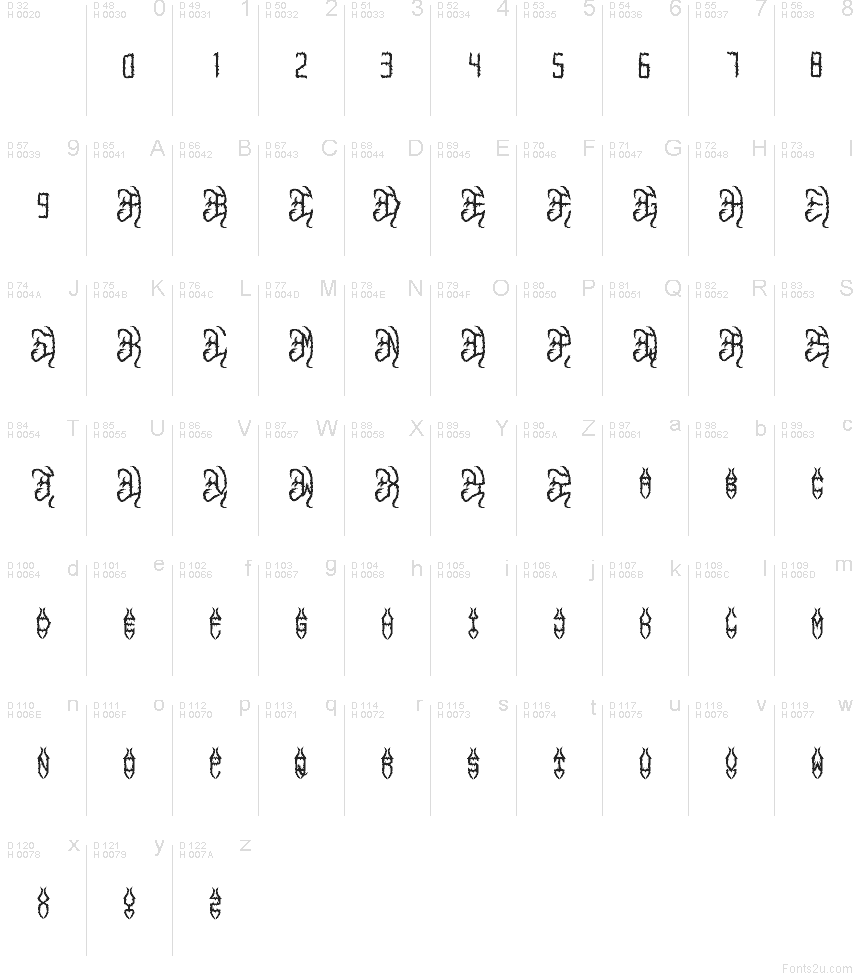
Horror Wings
Horror Wings — це безкоштовний готичний дисплейний шрифт із гострими штрихами, що нагадують крила, та виразними формами блеклеттера. Літери складаються у високі загострені арки із завитками, а нерівні, колючі краї надають накресленню зловісного, викарбуваного вигляду.
Horror Wings — це безкоштовний шрифт, який чудово підійде для постерів до фільмів жахів, оформлення метал-гуртів, запрошень на Геловін, готичних логотипів, вивісок для будинків із привидами та заголовків похмурих заходів. Його кутастий ритм і декоративність дозволяють шрифту виглядати ефектно навіть у коротких словах чи поодиноких написах.